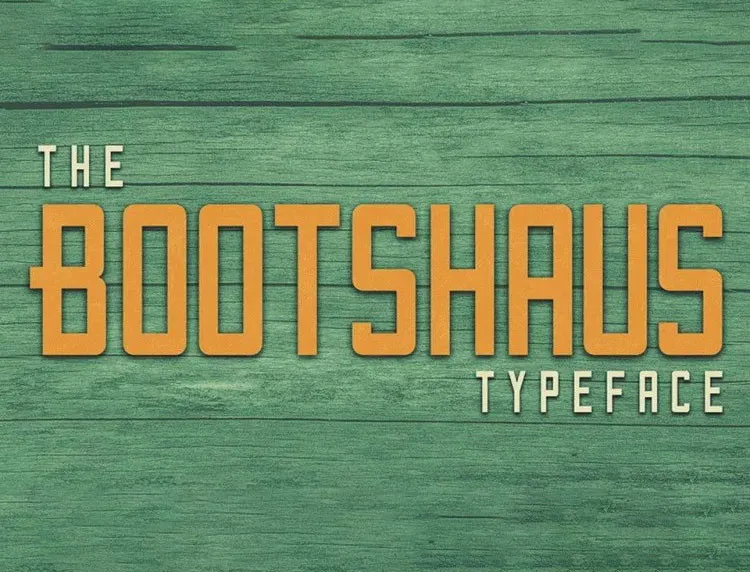
Bootshaus é uma fonte display experimental projetada pelo Felix’s Foundry que traz um toque de modernidade às páginas de sua revista ou ao título do seu novo site. Com suas formas retangulares e linhas redondas, esta fonte apresenta um contraste visual interessante entre os ângulos agudos e as curvas leves, criando uma harmonia elegante que se destaca em qualquer aplicação. Seu equilíbrio perfeito entre as pontas fortes dos ângulos e as linhas suaves das curvas a torna um recurso indispensável para headlines e design de título, oferecendo ao mesmo tempo o impacto poderoso necessários para destacar seu conteúdo em grande estilo. Escolha Bootshaus quando busca uma fonte que se destaca com sua simplicidade elegante e personalidade forte, projetada para criar um olhar atento sobre seus designs.